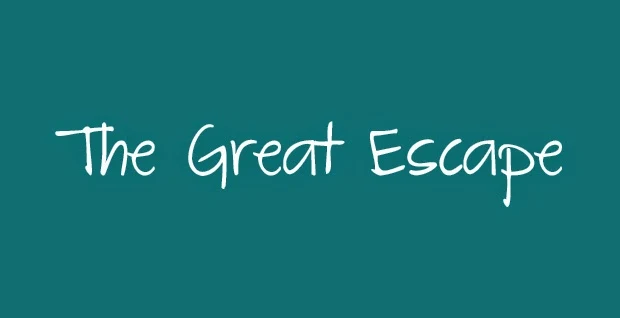
خط The Great Escape خط جميل ، حيت يظهر كأنه مكتوب باليد ، و سبق أن استعملناه في درس ” درس 108 : عمل ملصق للأطفال بإستعمال PhotoShop + ملف PSD” ، يمكنك تحميل هذا خط من رابط أسفله …